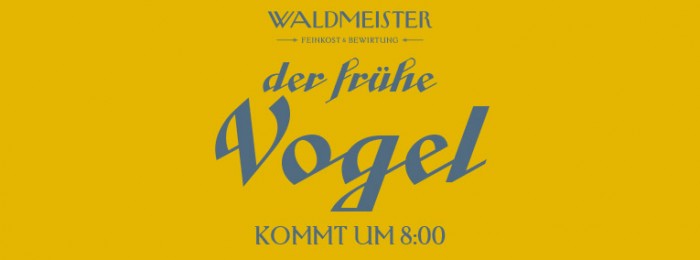
Retroschrift gesucht - welche Schrift ist das?
ich suche die Schrift, in welcher die Worte "der frühe Vogel" geschrieben sind.
Kennt jemand diese Schrift? Woher kann ich sie bekommen?
Sicher könnte man die Cabarga Cursiva mit einem Vektorgraphikprogramm manuell füllen.
Aber es gibt auch mehrere Schnitte der Cabarga Cursiva von ICG. Hier scheint es sich um die Cabarga Curs ICG Solid zu handeln, denn die Cabarga Curs ICG Solid Alt hat ein anderes „h“.